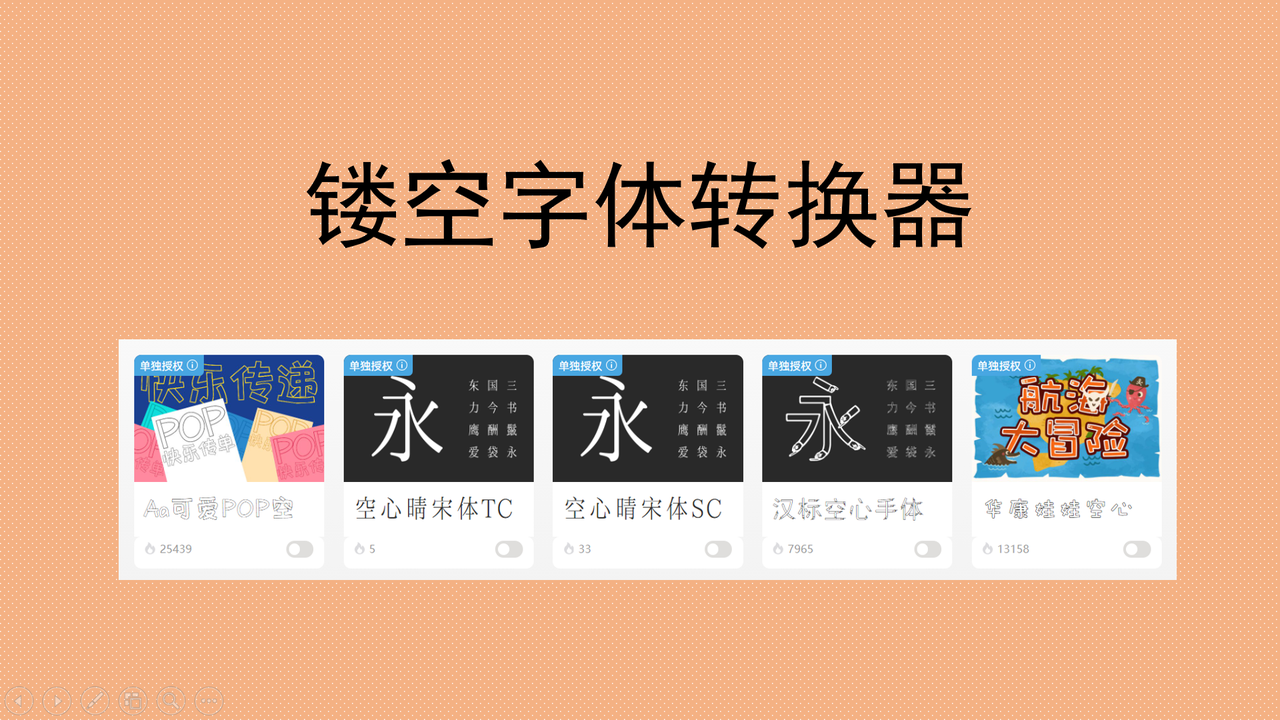
免费镂空字体在线转换,输入文字秒生成可复制空心艺术字
怎么样能让文字更加具有视觉冲击力?镂空文字效果绝对是最直接有效的选择。想要把普通文字快速转换为镂空艺术字,用设计软件太费时间费精力。今天就给大家带来一份宝藏清单:5 个免费镂空字体在线转换工具,输入文字就能一键转换成空心艺术字,不用安装软件,无需掌握高超的设计能力。无论是需要复制粘贴的线上文字,还是需要二次利用的高清图片素材,这些镂空字体在线转换器都能满足你的需求。每款工具都会有一些自己独特的优势,一起来看看你最适合哪一款吧,在线打造满意的镂空字体!
一、字由
提到字体转换器,很多设计师第一时间想到的都是字由,特别是在做镂空艺术字的时候,不需要自己手动描边。用户只需要进入字由的官网,然后在字体资源页面里面搜索“空心”,我们就可以得到一系列镂空艺术字的模板。点击自己喜欢的风格,在文字详情页面输入自定义文本内容,即可在线完成镂空字体转换。最关键的是,字由的字体资源都清晰标注了授权类型,不管是个人使用还是免费商用,你都能找到对应的字体,完全不会有任何的侵权问题出现。另外一种转换方式就是通过字由客户端,用户可实现在 PS、AI、ID、XD、Figma、Sketch、CDR 等设计软件中一键转换镂空字体效果,无需下载安装字体包,即可完成字体应用。目前市面上很多字体转换器,字由不仅能转换空心字体,更是一个专业且实用的字体管理神器,大家一起来体验一下吧。
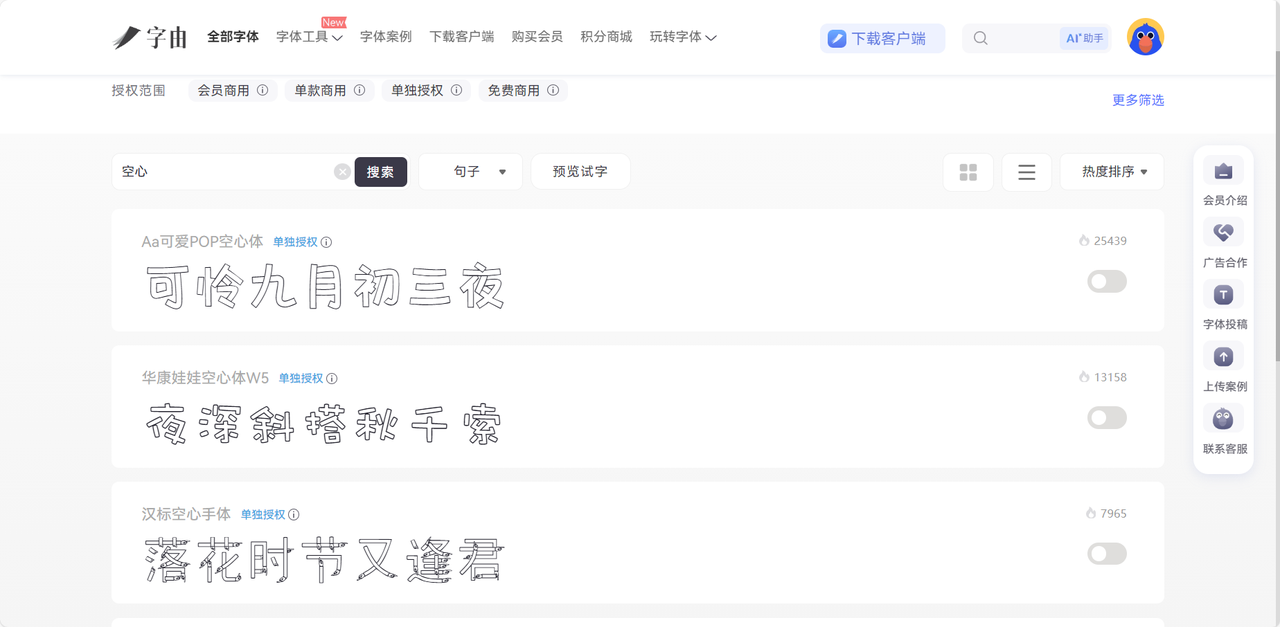
二、MockoFun
MockoFun 是一个功能非常全面的专业级平面设计网站,但它不需要你你有非常高超的设计能力,在浏览器打开官网就能将常规的英文字体转化为空心字体。MockoFun 最大的特点就是可以自由设置轮廓,也就是说当你在画板中输入文字内容后,上方菜单栏会弹出对应的按钮,辅助你去自由调节文字描边的宽度,极简的设计的外轮廓线或者是厚实的粗重立体边框都能一键实现,甚至可以调整颜色、透明度、过渡程度、边缘变化等更加细节的内容。如果你需要那种偏向游戏风格的极具科技感的精致镂空字体,MockoFun 还支持点状拐角和高光质感的调节,你完全可以在该网站内制作出一款你满意的镂空字体。转换完成的镂空字体可以直接下载为 PNG 格式,直接拖拽或导入到其他设计软件内二次使用是非常方便的,轻松打造极具辨识度的视觉作品。
三、TextToolz
想要将镂空字体直接发布在各大社交媒体平台或是聊天框,不需要下载图片,直接就想要文字版,那么 TextToolz 是是适合你的一款镂空字体生成器。和大多数的字体工具不同,它使用的是 Unicode 字符映射规则,输出的是可以直接复制粘贴的文本字符。用户打开页面智慧,只需要在文本框内输入文字内容,选择你喜欢的样式,点击生成按钮即可获得一个镂空字体,直接复制就能使用,几乎兼容所有系统和设备。大家完全可以放心的是,TextToolz 页面采用极简模式,不会有多余的广告弹窗,不存在莫名其妙的注册环节,也不会强制要求你充会员体验功能。对于喜欢在社交主页中彰显个性但预算有限的年轻设计师来说,TextToolz 让人欲罢不能!
四、FontBolt
FontBolt 是一个综合性的镂空英文字体展示平台,它更侧重于预览和本地保存管理镂空字体资源。这里的镂空字体资源风格丰富且排列整齐、分类清晰,比如无衬线镂空字体、发光镂空字体、泼墨镂空字体等等,商务的简约的还是酷炫的,你在这里都能找到对应的镂空字体资源,一键完成字体转换。最值得一提的是,FontBolt 支持一键下载镂空字体到各种设备中,对于那些经常跨平台协作的设计团队尤其友好!还可以快速用它输出高清镂空字体预览图,嵌入会议文档中直接用于会议讨论,在办公环境中可谓是帮了大忙。除此之外,还有一部分字体 FontBolt 提供完整的 TTF 或 OTF 字体包下载链接,这意味着你可以把喜欢的镂空字体下载并永久安装到你的电脑里,后续想用的时候随时都能调用。
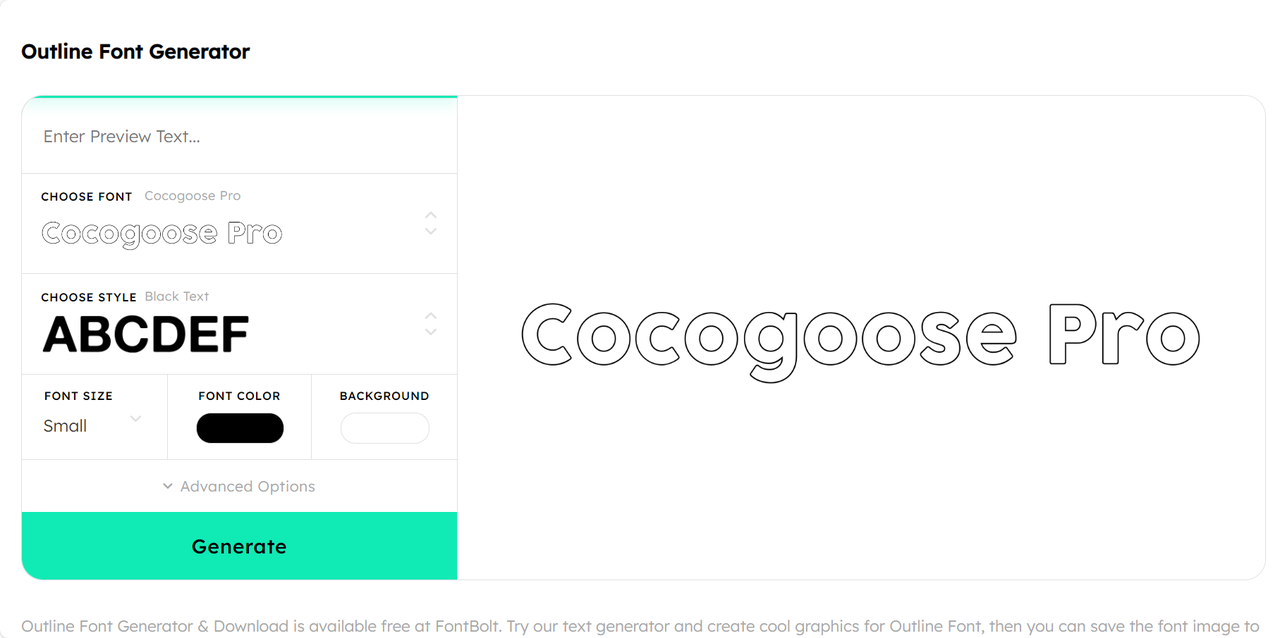
五、A.Textools Hollow Text Generator
相较于上面四个镂空字体在线转换器,A.Textools Hollow Text Generator 更加具有隐私性和安全性。比如你输入文字并转换到空心字体的这个过程中,其他工具或许会有数据残留和记录,但它会优先在浏览器内完成所有字体转换,不会有任何个人数据残留,尤其适合制作保密商业设计的用户,安全感拉满。这这个工具的界面设计非常简单明了,一个文本输入框再搭配一个风格预览区,即使是英文页面,用户也能看懂如何使用。和 TextToolz 类似,这个工具也是输出纯文本格式的空心字符,可以直接复制到 Word 文档、社交平台文字框等,字体兼容性也很高,主流平台都能正常显示镂空字体效果。A.Textools Hollow Text Generator 还贴心地为大家提供了识别功能,如果你有很感兴趣的特殊样式字体,但不知道它是由哪些符号元素组成的,也可以直接复制到这里进行检索哦,我之前试过几次,结果比较准确,可以自己试试。